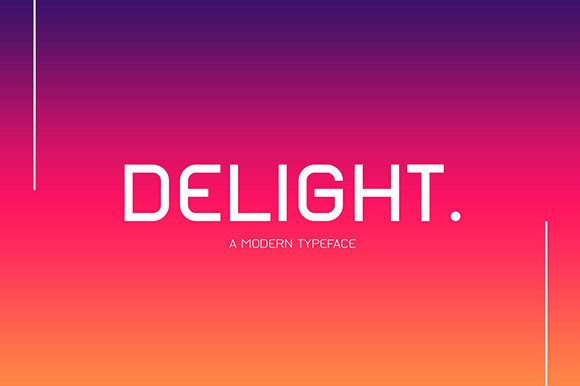
Creativefabrica Delight Font
[Creativefabrica] Delight Font
Шрифт Delight - это современный шрифт без засечек.
Подходящий для широкого спектра дизайнов благодаря своему аккуратному и простому стилю, этот шрифт имеет потенциал стать Вашим любимым шрифтом, неважно по какому поводу!